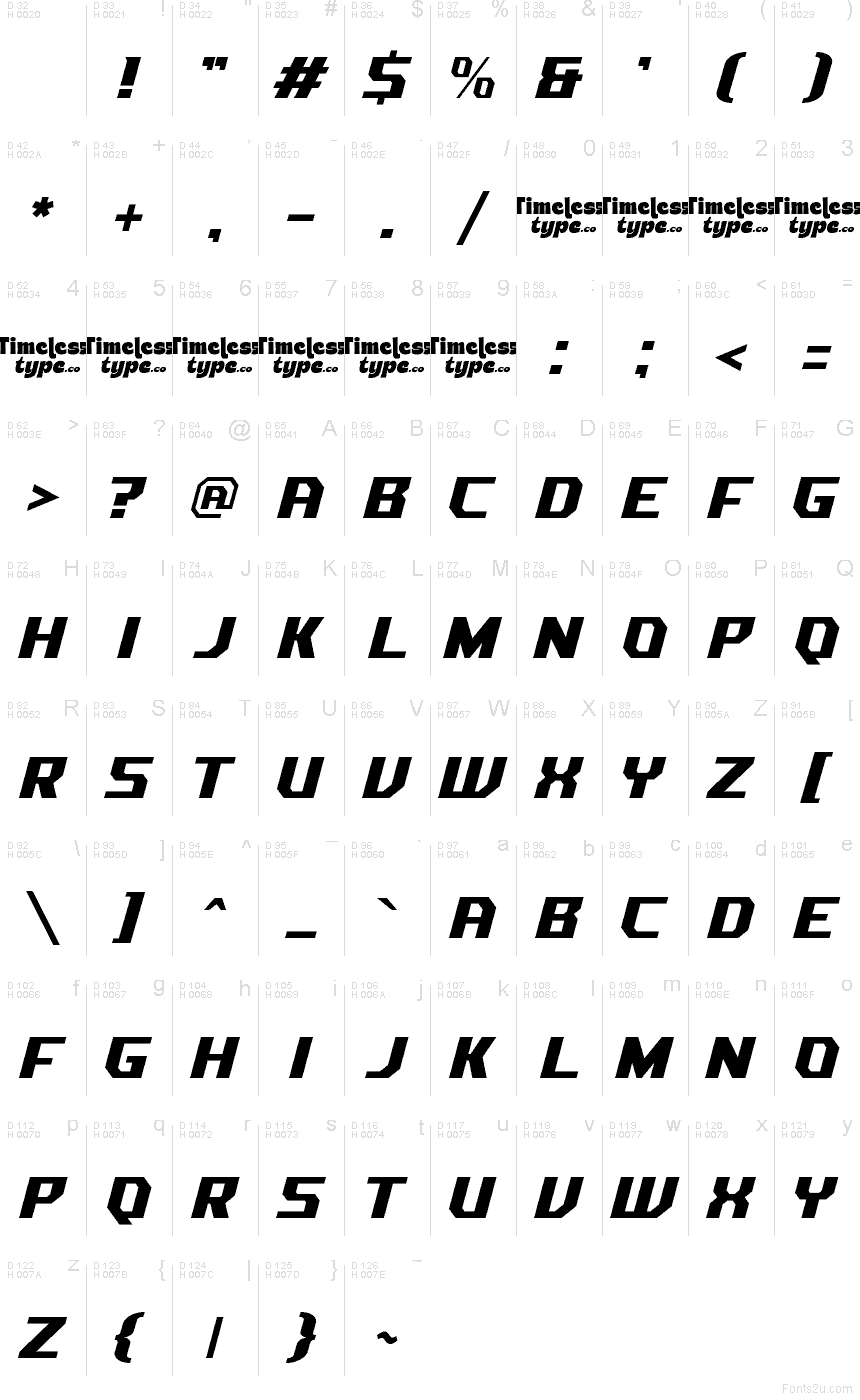
Sound Wave von TimelessType.co ist eine kostenlose Techno-Display-Schrift mit scharfen, nach vorne geneigten Großbuchstaben und einer Ästhetik von präzisem Metallschliff. Die Buchstaben bestehen aus harten Winkeln und abgeschrägten Ecken, was der Schrift einen schnellen, technoiden Rhythmus verleiht. Das Design erinnert dabei weniger an neutrale Schriften, sondern eher an Maschinenbau, Rennsport-Grafiken und frühen digitalen Futurismus.
Sie passt perfekt zu Game-Logos, Flyern für elektronische Musik, Sport-Branding, Sci-Fi-Titeln und Plakatüberschriften, bei denen es auf Schnelligkeit und Charakter ankommt. Als kostenlose Schrift eignet sie sich zudem hervorragend für Cover-Texte und prägnante Wortmarken, da die engen, geneigten Formen selbst bei kurzen Wörtern eine dynamische Bewegung erzeugen.